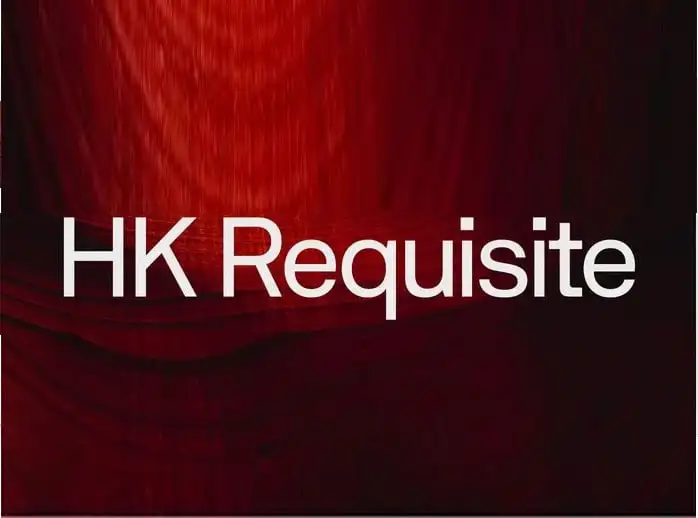
HK Requisite Sans Serif Font – Download Grátis
A HK Requisite Sans Serif é uma tipografia casual e moderna, projetada para agregar beleza e simplicidade sem perder elegância. Inspirada na compactação do Neue Haas Grotesk e no forte carácter de Akzidenz Grotesk, esta fonte apresenta detalhes atuais que a tornam perfeita para qualquer projeto visual contemporâneo. Com sua forma um pouco mais larga, essa fonte parece ainda mais casual, permitindo-lhe explorar diferentes estilos em seus projetos e designs. Seja você desenvolvendo material gráfico para o site de uma empresa ou criando um layout minimalista para redes sociais, a HK Requisite Sans Serif pode ser sua escolha ideal. Inspirada no nome dos elementos essenciais que levam ao atingimento do objetivo, essa fonte é certamente indispensável para aqueles que desejam incorporar um toque de modernidade e casualidade em seus projetos visuais.